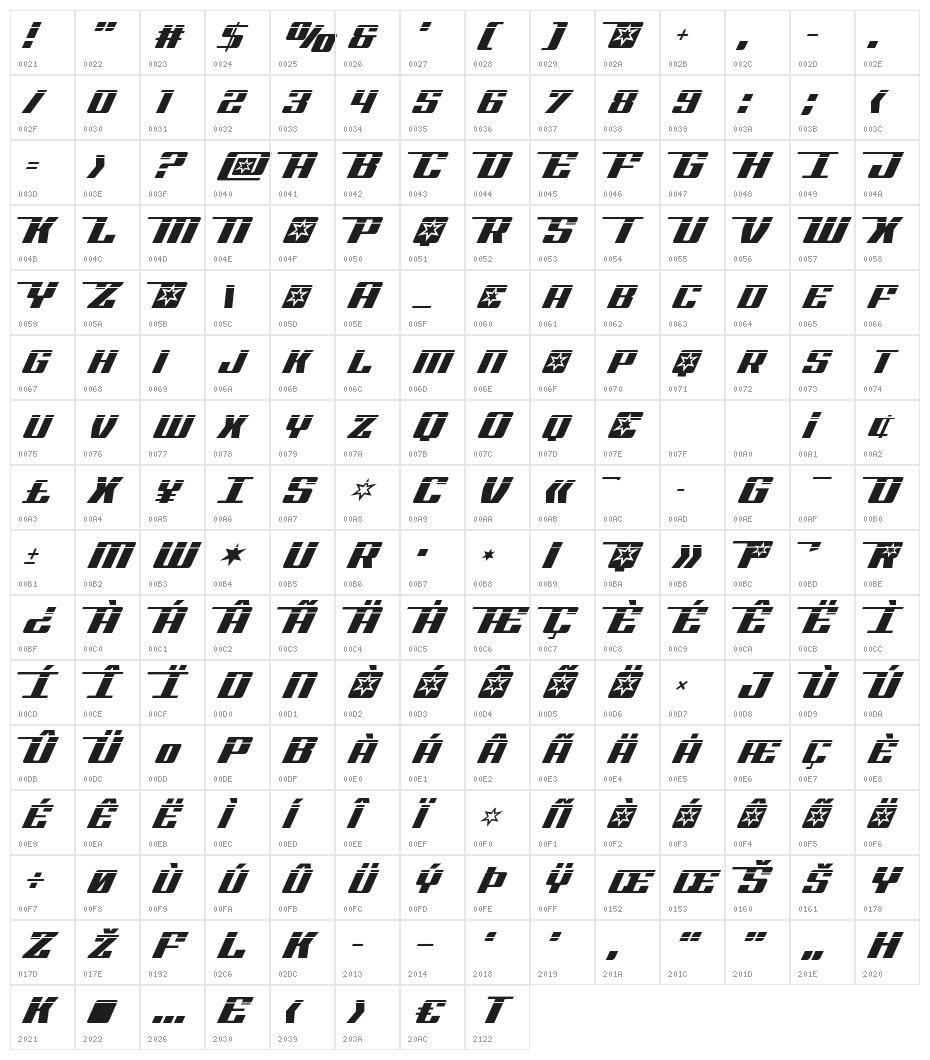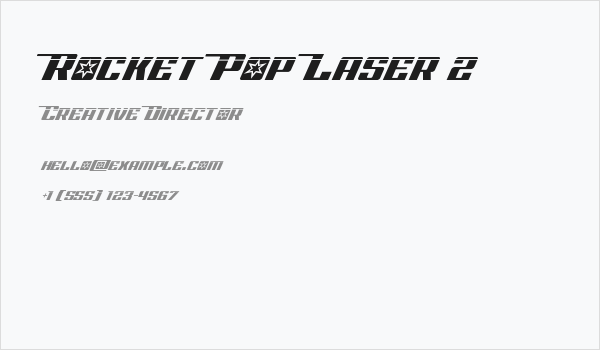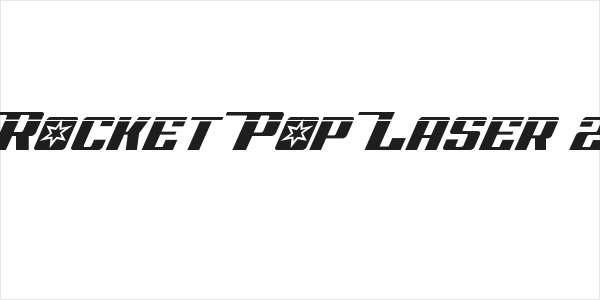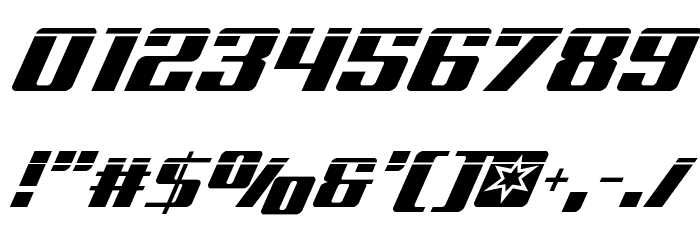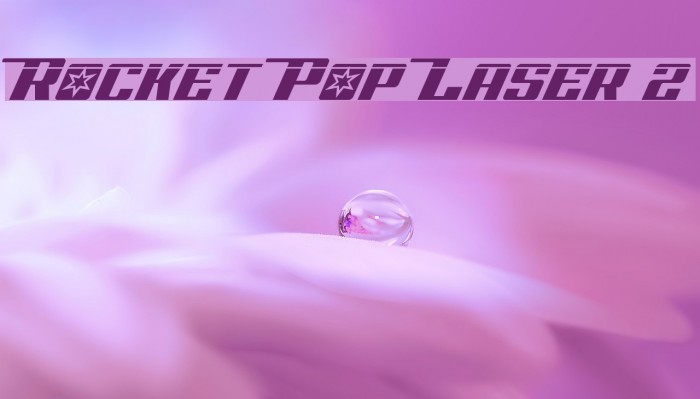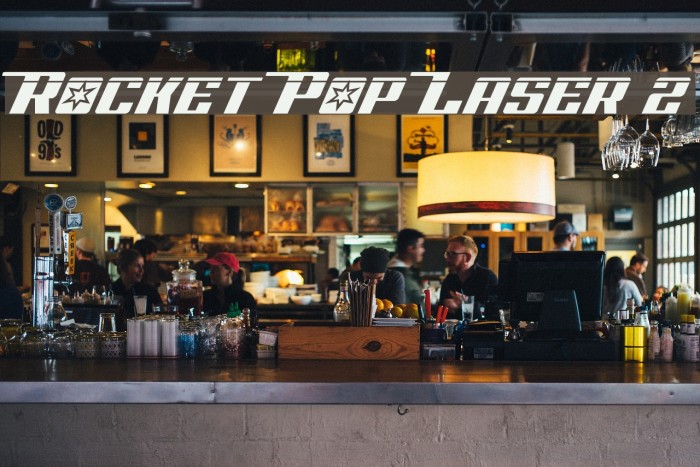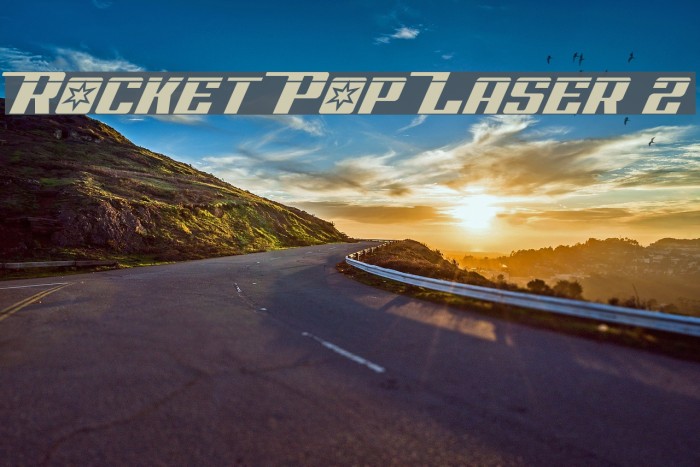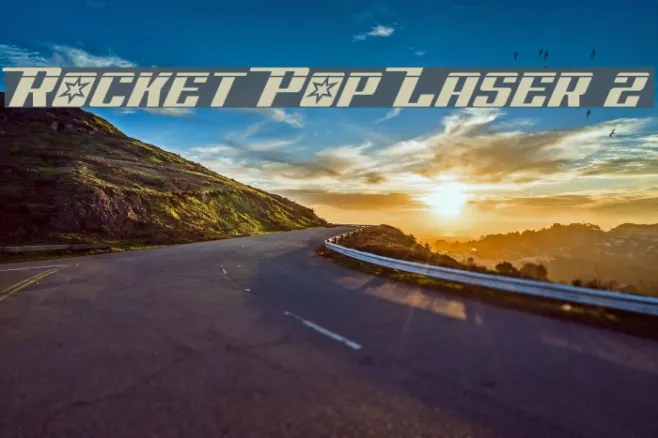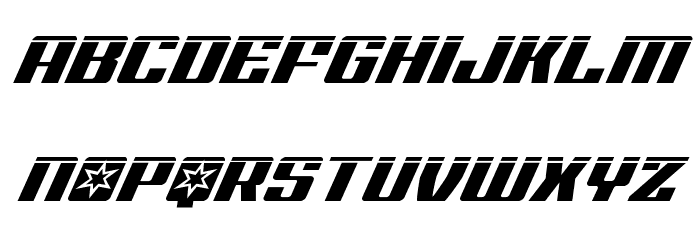
Rocket Pop Laser 2 Font
| Proyectos propuestos | Ideal for sci-fi themed posters, video game titles, branding for tech companies, or any project needing a modern, energetic typeface. |